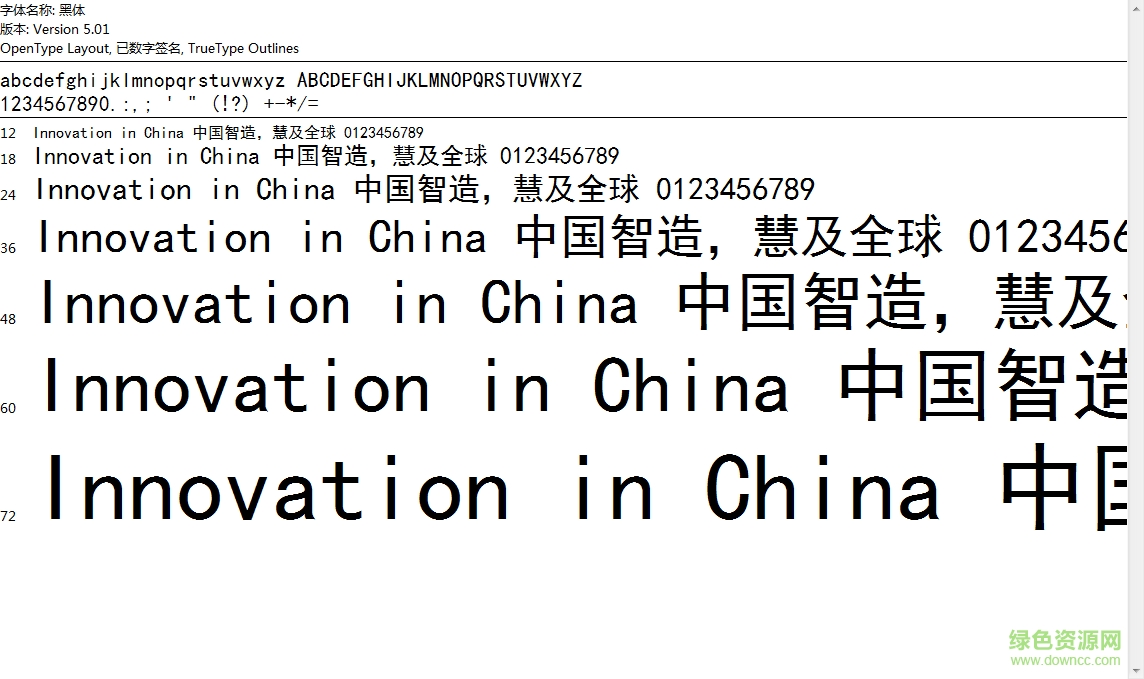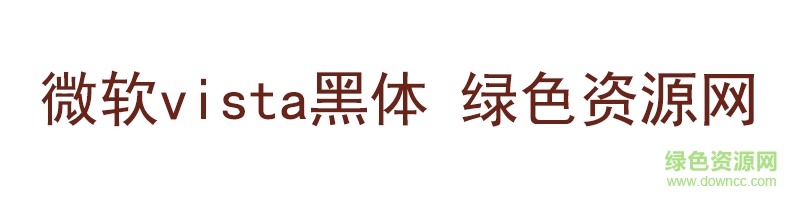
微軟vista黑體是一款簡潔美觀的win字體,此款字體粗細均勻,大小適中,整體效果非常出眾,廣泛的應用于屏幕設計、包裝印刷、廣告設計等領域,綠色資源網提供最全最新的中英文字體素材,歡迎下載使用!
微軟vista黑體是中國第一款突破鉛字黑體束縛的原創(chuàng)黑體,在同類產品中筆形特征典雅現代,結體豐富容易辨識,獨具匠心的筆畫與結構的微妙結合體現出黑體獨有的字形之美,展現漢字所具有的多變、精巧的靈韻之美。